Schriftschnitt
Typografischer Fachausdruck aus dem gewerbespezifischen Sprachschatz dspr. Schriftschneider, Schriftgießer, Schriftsetzer und Drucker aus der Periode des materiellen Schriftsatzes mit physischen Drucktypen aus Metall (z.B. aus einer Blei-Zinn-Antimon-Kupfer-Legierung) für eine Schriftstilvariante einer physischen Druckschrift innerhalb einer Schriftfamilie oder ggf. Schriftsippe; Schriftstilvariante einer Druckschrift bzw. nzl. auch eines Fonts; nzl. »Schriftstil«; eng. »Font Style«.
Neben gestalterischen und historischen Wesenszügen einer Druckschrift römischen Ursprungs zählen insbesondere die
- Schriftbreite (z.B. schmal oder breit)
- Schriftlage (z.B. normal oder kursiv)
- Schriftstärke (z.B. mager oder fett)
zu den wesentlichen Schriftklassifikationsmerkmalen. In Kombination von differenten Schriftbreiten, Schriftlagen und Schriftstärken ergeben sich bei Druckschriften bzw. Fonts vielfältige Schriftstilvarianten.
Abgeleitet werden die Schriftstilvarianten immer von der Grundschrift einer Schriftfamilie. Bei Werksatzschriften (Mengensatzschriften) ist das in der Regel ein Schnitt mit einer normalen Schriftbreite (Basisschriftbreite), einer normalen vertikalen Schriftlage (Basisschriftlage) und einer normalen Schriftstärke (Basisschriftstärke); wobei sich der Begriff »normal« – was ist schon normal? – auf jahrhundertalte Traditionen und Erfahrungen in der Schriftgestaltung von Antiqua-Schriften und deren Lesbarkeit bezieht.
Beispielsweise versteht man unter »kursiv halbfett« eine Schrift mit normaler Schriftbreite in kursiver Schriftlage und halbfetter Schriftstärke. Oder unter »Kapitälchen schmalmager kursiv« eine Variante in Form von Kapitälchen in schmaler Schriftbreite, in einer kursiven Schriftlage und mit einer mageren Schriftstärke. Ähnlich verhält es sich mit int. Termini.
Semantisch rührt der Begriff »Schriftschnitt« von »Schrift schneiden« her, denn die Protoform einer physischen Druckschrift wurde in Deutschland ab Mitte des 15. Jahrhunderts mit der Erfindung des »Handgießinstruments« bis zur Erfindung der »Stempelschneidemaschine« Ende des 19. Jahrhunderts von einem Schriftschneider, Formschneider, Goldschmied oder Stempelschneider händisch in Metall geschnitten. 1)
Die Bezeichnung »Schriftschnitt« wird nach wie vor aus traditionellen Motiven in Deutschland, Österreich und der dspr. Schweiz auch für digitale Fonts verwendet, wobei sich der Terminus »Schriftschnitt« streng genommen nur auf physische Drucktypen bezieht. Der nzl. Begriff »Schriftstil« bezieht sich hingegen sowohl auf physische (z.B. aus Metall oder Holz) als auch auf optomechanische (z.B. auf Lithofilm) und digitale Schriften (Fonts). Allerdings ist im typografischen Sprachgebrauch der Begriff »Schriftschnitt« immer konkret, der Terminus »Schriftstil« kann hingegen mehrdeutig sein (siehe Schriftstil, 2. Punkt).
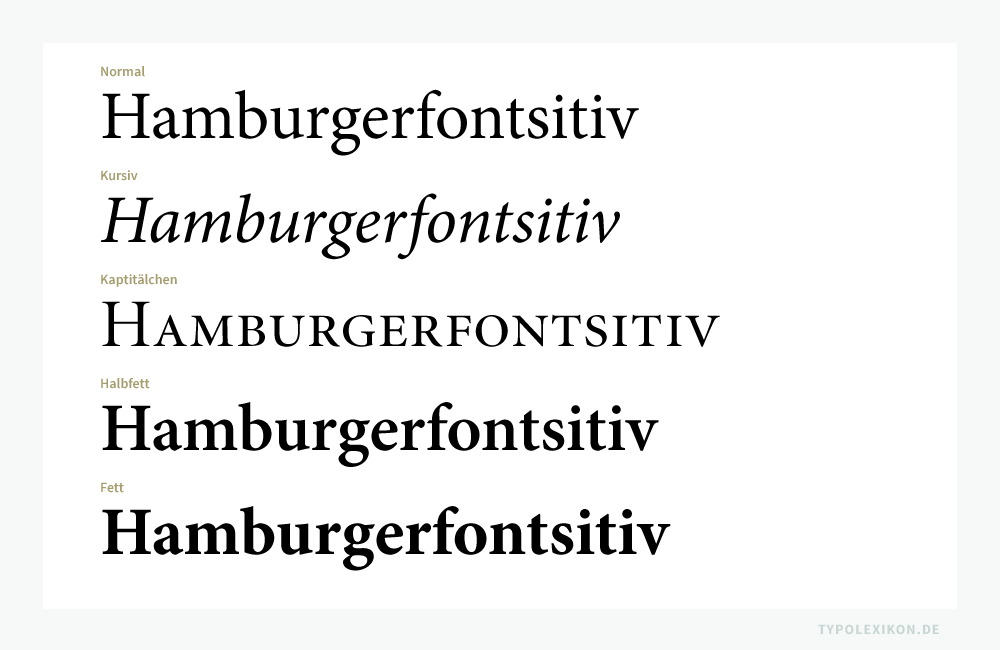
Gewöhnliche Schriftschnitte bzw. Schriftstile bei Druck-, Screen- und Webfonts:
| Schriftschnitt (deu.) | Schriftstil (int.) |
| breit | ancha bred extended large largo |
| breitfett | bredfet bold extended large gras negra ancha nero largo |
| breithalbfett | bredhalvfet large demigras medium extended neretto largo seminegra ancha |
| breitmager | bred mager chiarissimo largo fina ancha light extended large maigre |
| buch | book libro romain labeur text (ggf.) |
| buch kursiv | book italic buch kursiv italique labeur libro corsivo libro cursiva |
| buch schmal | book condensed buch smal étroit romain lebeur libro estrecha libro stretto |
| eng | condensed étroit estrecha strettissimo trång |
| extrabreit | extra-wide |
| extrafett | extra bold extrafet extra gras extra heavy muy negra nerissimo |
| extrafett schmal | étroit extra gras extra bold condensed extrafet smal muy negra estrecha nerissimo stretto |
| extraleicht | extra light |
| extramager | extra thin |
| fett | bold fet gras negra nero |
| halbfett | alvfet demi-bold demi-gras neretto semibold seminegra |
| Kapitälchen fett | Caps bold |
| Kapitälchen kursiv | Caps italic |
| Kapitälchen leicht | Caps Display |
| Kapitälchen normal | Caps Capitales Kaptäler Maiuscoletto Mayusculita |
| kursiv | corsivo cursiva italic italique |
| kursiv extra | extra bold condensed italic italique étroit extra gras muy negra estrecha cursiva nerissimo stretto corsivo |
| kursiv fett | bold italic italique gras kursiv fet negra cursiva nero corsivo |
| kursiv halbfett | italique demigras kursiv halvfet medium italic neretto corsivo seminegra cursiva |
| kursiv mager | chiarissimo corsivo fina cursiva italique maigre light italic |
| kursiv schmal | condensed italic estrecha cursiva italique étroit kursiv smal stretto corsivo |
| kursiv schmalhalbfett | italique étroit demi-gras kursiv schmalhalvfet medium condensed italic neretto stretto corsivo seminegra estrecha cursiva |
| kursiv ultraleicht | cursiva muy fina italique ultra maigre kursiv ultra mager ultra chiaro corsivo ultra light italic |
| leicht | light |
| leichthalbfett | medium |
Schriftschnitte können darüber hinaus in »Optische Größen« (Caption, Regular, Subhead und Display) eingeteilt werden, also in Gruppen mit speziellen Typometrien, die vom Schriftgestalter:in (Type Designer) im Rahmen eines Schriftgradabstufungsmodells speziell auf Konsultationsgrößen, Lesegrößen, Schaugrößen und Ferngrößen bzw. Plakatgrößen abgestimmt wurden. Im dspr. Raum werden diese Schriftschnitte oft auch als »Designgrößen« bezeichnet (eng. »Optical Sizes«).